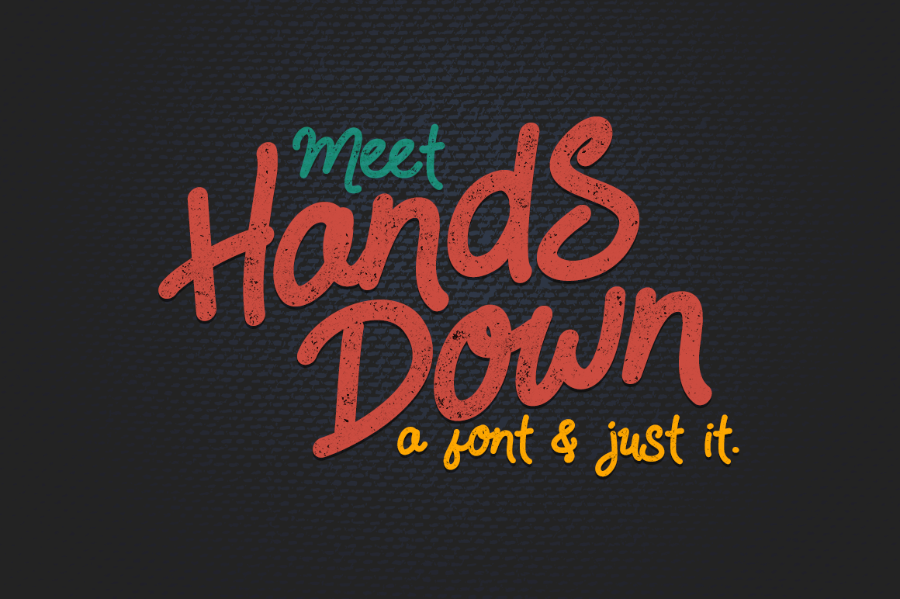
Hands Down Font
A Hands Down Font é uma elegante escolha para quem busca um script fluido que flui naturalmente no design. Criada cuidadosamente pelo designer Hamilton e inspirada nas mãos que escrevem, esta fonte foi projetada especialmente para dispositivos iPad. Ela combina simplicidade com modernidade, sendo tão simples quanto pode ser uma fonte script — até o ponto de não incluir alternativas ou ligaturas complexas. Uma surpresa inesperada é seu suporte a múltiplas línguas, tornando-a ainda mais versátil para diferentes projetos. Se você estiver procurando por uma fonte que dê um toque especial em suas criações gráficas — seja em embalagens de produtos, materiais promocionais, cartazes e convites, até mesmo na personalização de websites ou revistas — a Hands Down Font é perfeitamente adequada. Se você já experimentar esta fonte, certamente amará sua facilidade de uso e beleza única. A Hands Down Font é uma ótima adição para seu portfólio de ferramentas gráficas, oferecendo design elegante com um toque natural da mão. Tente-a agora e descubra por si mesmo o porque tantos profissionais estão se impressionando cada vez mais com esta fonte.